Aldusblatt
Blumenartiges Alinea; einzelnes Zierornament in Form eines herzförmigen Efeublattes; Schmuckzeichen; dekorative Glyphe im Zeichensatz eines Fonts. Der Terminus »Aldusblatt« ist ein Synonym für das »Hederablatt« (lat. »Hedera« für »Efeu« bzw. »hedera folium« für »Efeublatt«); Hedera-Zeichen; Kurzform Hedera. Ugs. auch als »Druckerherz« oder »Druckerblume« bezeichnet.
In der typografischen Schriftklassifikation gehört das Aldusblatt (Hederablatt) zu den floralen Alineas bzw. zu den »Fleurons« (frz. »fleuron« für »Schmückendes« von» fleur« für »Blume«), also zu den blumenartigen Zierornamenten. In der Paläografie ist das kalligraphische Hedera in lateinisch- und griechischsprachigen Handschriften eine Alinierung, um Absätze kenntlich zu machen.
Das »Aldusblatt« wurde nach dem venezianischen Humanisten, Verleger und Typografen Aldus Manutius (dem Älteren, 1449–1515) benannt, der dieses florale Alinea gerne als Schmuckzeichen, Trenn- und Schlussstück in seinen Aldinen verwendete.
Da Aldus Manutius sich insbesondere der Wiederbelebung klassischer Handschriften, insbesondere den Klassikern der griechischen und römischen Literatur widmete, liegt die Vermutung nahe, dass er mit dem Hedera-Zeichen typografisch die blumenartigen Zierornamente imitierte, die in der Kalligraphie seit Anbeginn üblich waren und die zum Standardrepertoire jedes versierten Kalligraphen gehörten.
So wurden beispielsweise u.a. Absätze in griechischen und lateinischen Handschriften und Büchern mit dem Hedera-Zeichen gegliedert. Das Hederablatt war also eine Art Interpunktionszeichen, das einen neuen Absatz bzw. einen Sinnschritt kenntlich machte. 1)
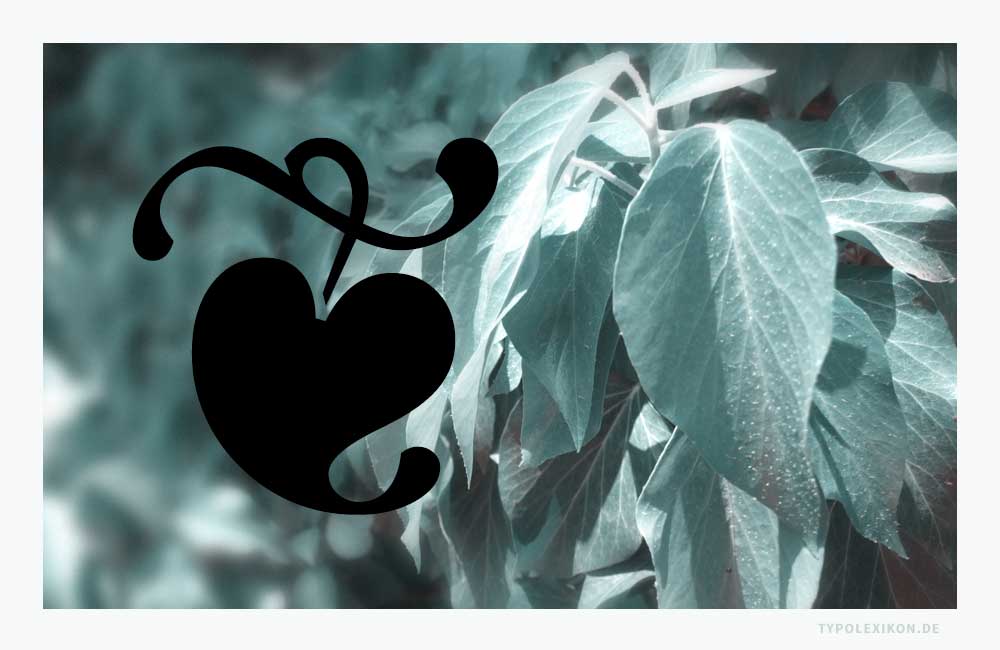
Allerdings war Aldus Manutius nicht der erste Typograf, der das Hedera-Zeichen verwendete. Bereits die Prototypografen Erhard Ratdolt (1447–1527/1528) 2) und Peter Schöffer (um 1425/1430–1502/1503) benutzten es in ihren Inkunabeln. Wer das Synonym »Aldusblatt« erstmals einführte, ist nicht überliefert. In der extratypografischen Literatur wird das Hedra-Zeichen vereinzelt auch als »Druckerherz«, »Druckerblume« oder fälschlicherweise als »Weinblatt« interpretiert. Die ursprünglich typische längliche Herzform veränderte sich im Zuge der Moderne hin zu einer eher rundlichen Form.
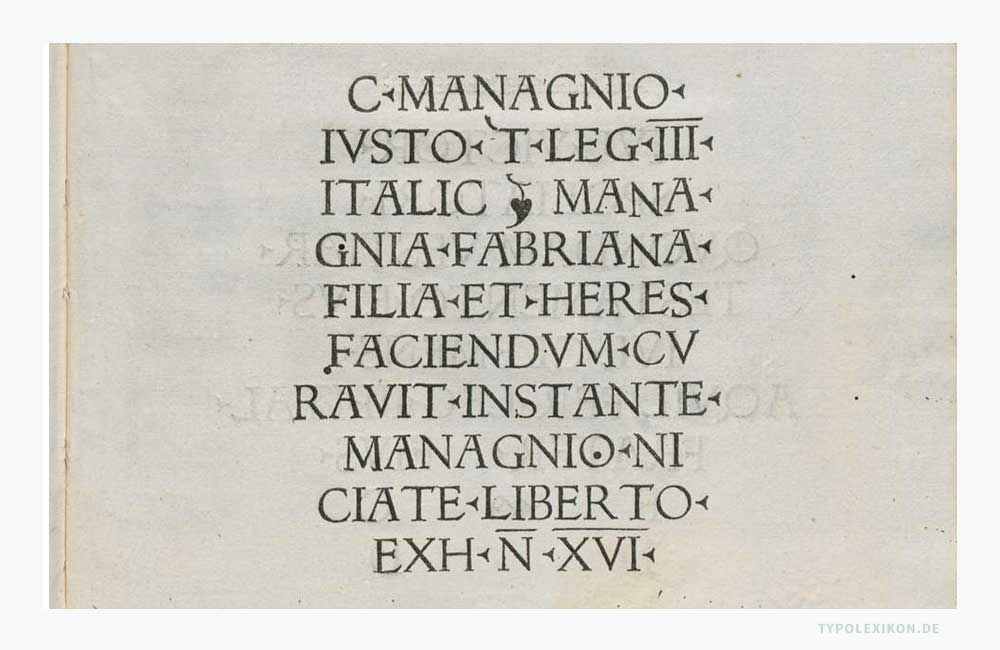
Die Sichtung von deutschen Schriftmusterbüchern für Zierrat, Blei- und Holztypen des 19. und 20. Jahrhunderts legt nahe, daß das Aldusblatt im materiellen Schriftsatz nahezu ausschließlich in der von der Antiqua geprägten Typografie üblich war, z.B. in der Italienischen, Französischen oder Englischen Typografie, jedoch nicht oder kaum in der von der Fraktur geprägten Deutschen Typografie.
Das Aldusblatt bzw. Hedera ist seit Jahrhunderten bis heute noch ein populäres Schlussstück in der Buchtypografie. Es wird es auch gerne von Druckereien, Buchhändlern und Verlagen als »Druckerblume«, Vignette oder als Signet verwendet, beispielsweise vom Verlag Hermann Schmidt in Mainz, der sich mit seinem Verlagsprogramm insbesondere auf die Typografie und das Grafikdesign spezialisiert hat. 3)
Das Aldusblatt in unterschiedlichen horizontalen und vertikalen (links- und rechsdrehend) Varianten findet sich heute in zahlreichen Fonts als Sonderzeichen, beispielsweise in den »ITC Zapf Dingbats« von Hermann Zapf (1918—2015) oder der »Minion Pro« von Robert Slimbach (*1956). 4)
| ↑1 | Anmerkung: Daher rührt – nebenbei bemerkt – auch der typografische Terminus »Alinieren« und »Alinea« (lat. »a linea« für »von der Zeile«) für »Abtrennen« bzw. »Abtrennung« bzw. »mit einer neuen Zeile beginnen«. Deshalb zählt das Aldusblatt auch zu den Alineas. |
| ↑2 | Quelle: Peutinger, Konrad: Romanae vetustatis fragmenta in Augusta Vindelicorum et eius dioecesi gedruckt, 1505 bei Erhard Ratdolt (1447–1527/1528), Inkunabeln der Bayerischen Staatsbibliothek, München, online verfügbar unter https://daten.digitale-sammlungen.de/~db/bsb00005801/images/index.html?id=00005801&groesser=&fip=qrssdaseayaqrsyztsyztseayaenxs&no=7&seite=9 (19.6.2017). |
| ↑4 | Anmerkung: Das vertikale »Floral Heart« hat unter UNICODE® den Code Point U+2766 und das horizontale »Rotated Floral Heart Bullet« den Code Point U+2767. |